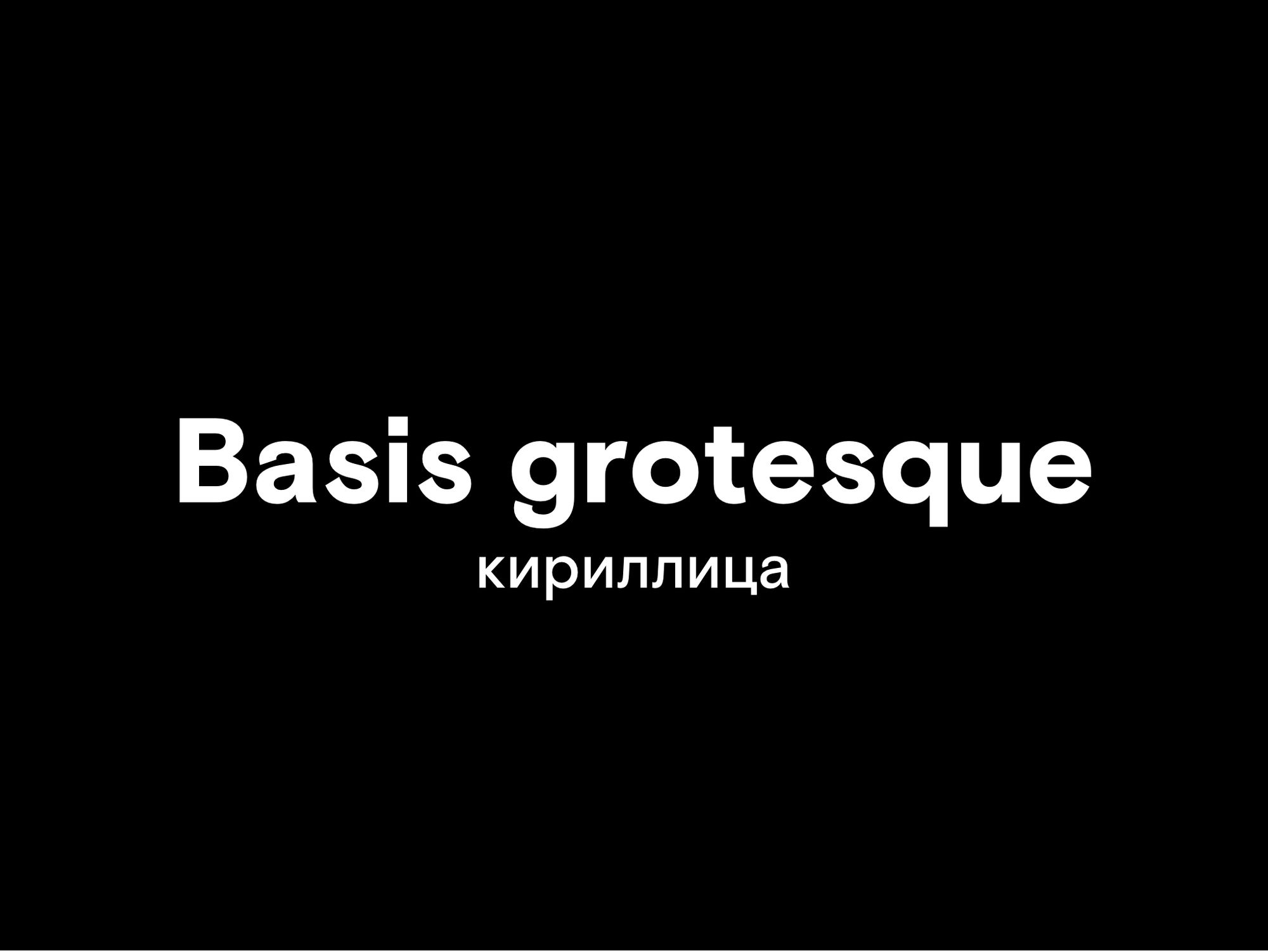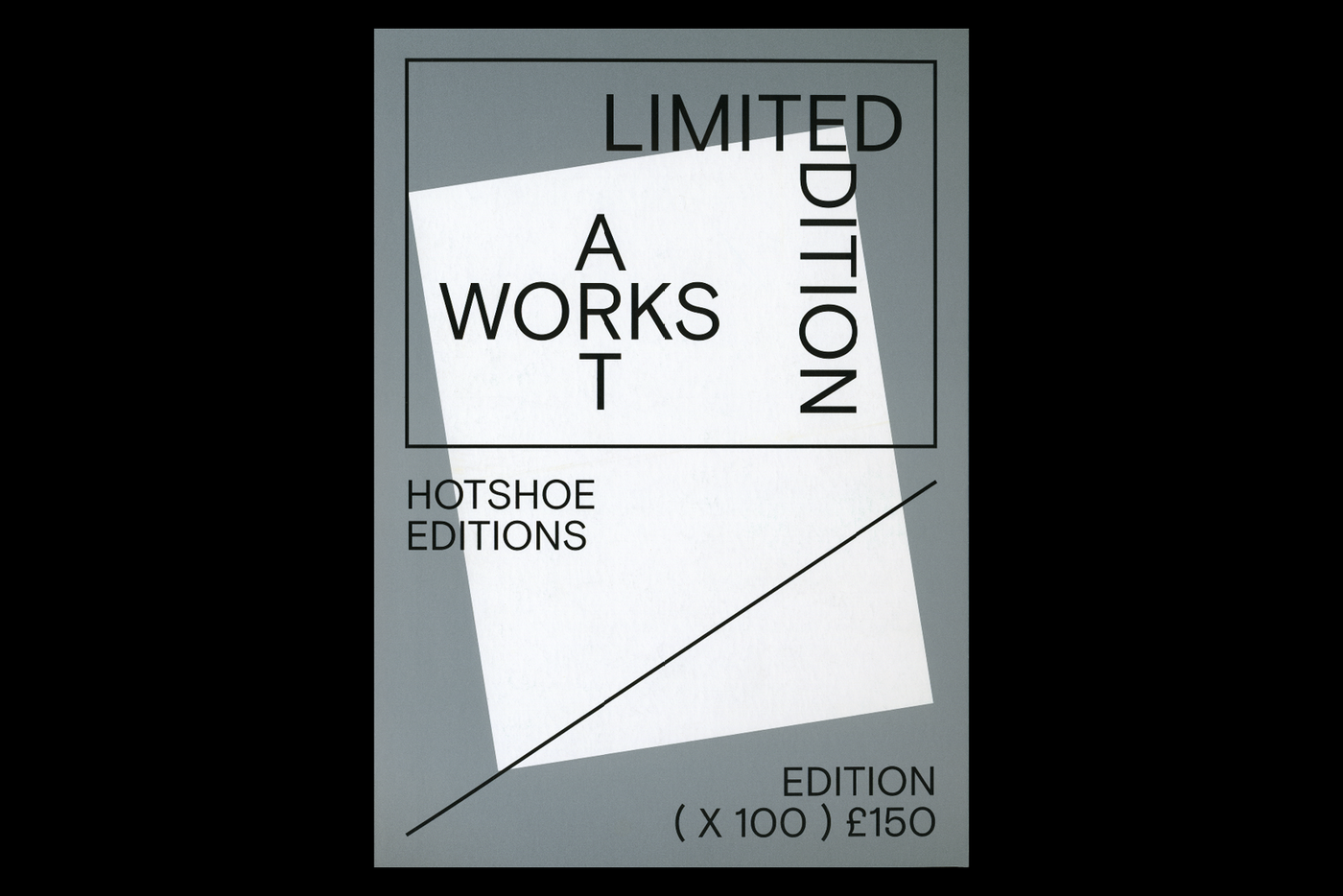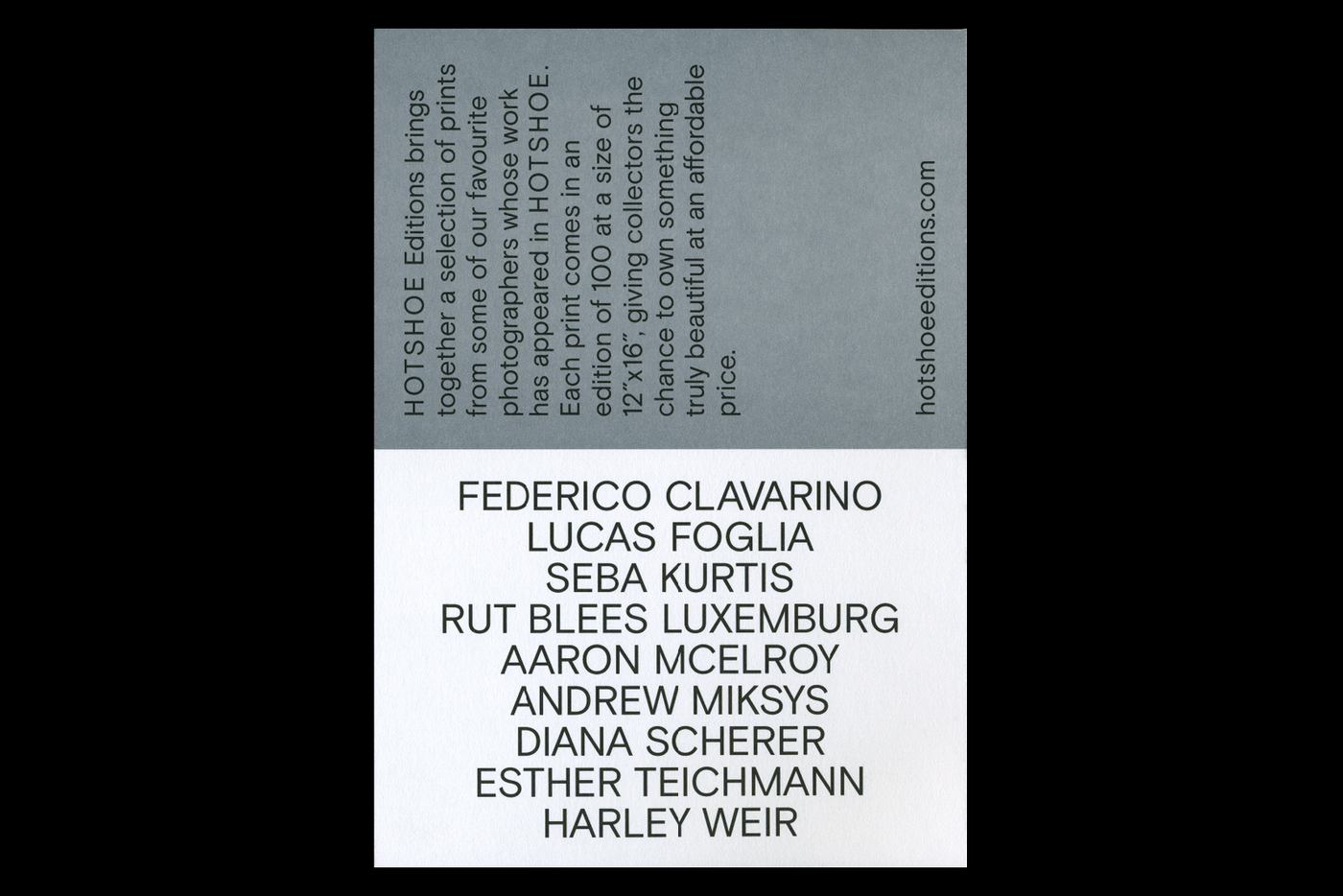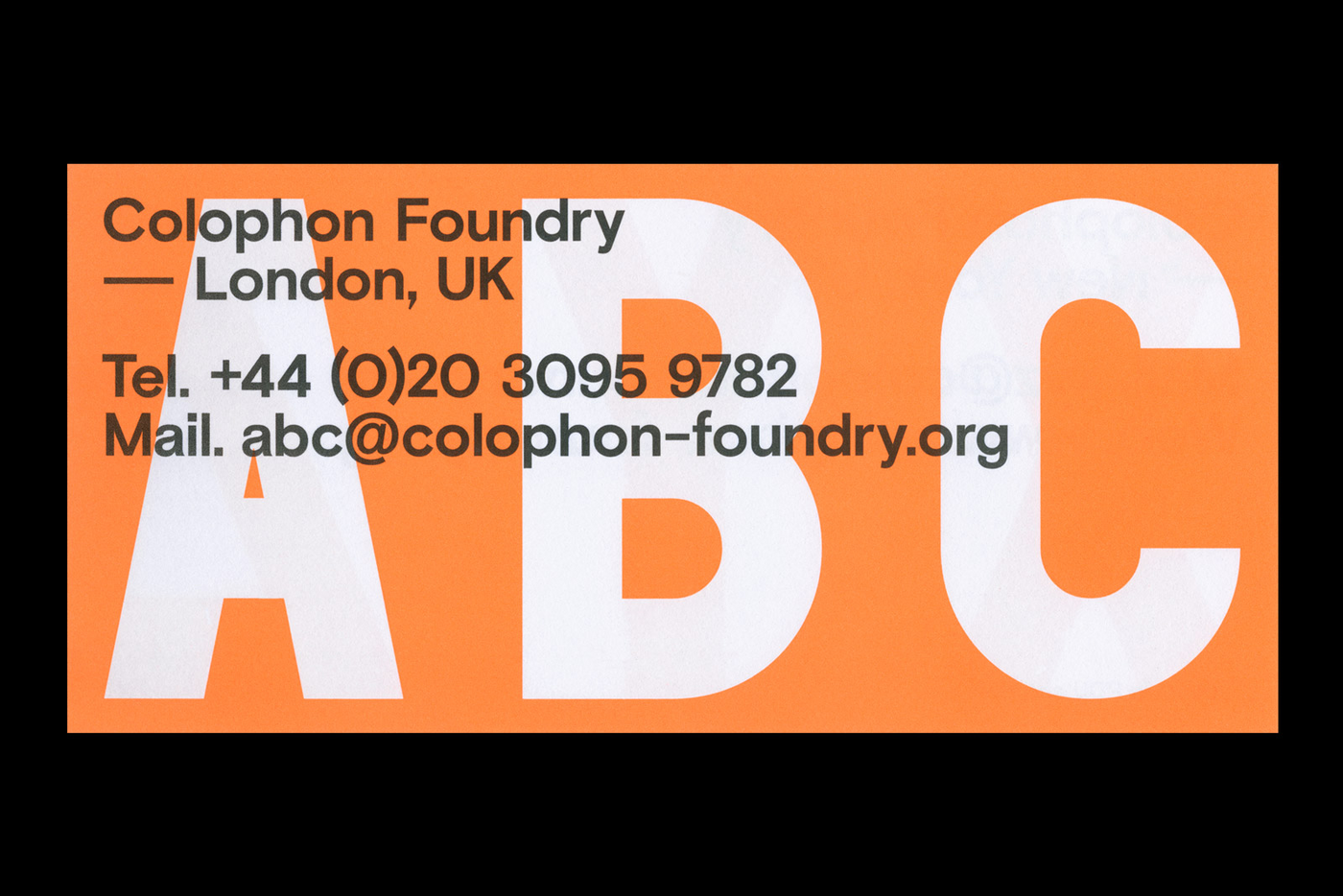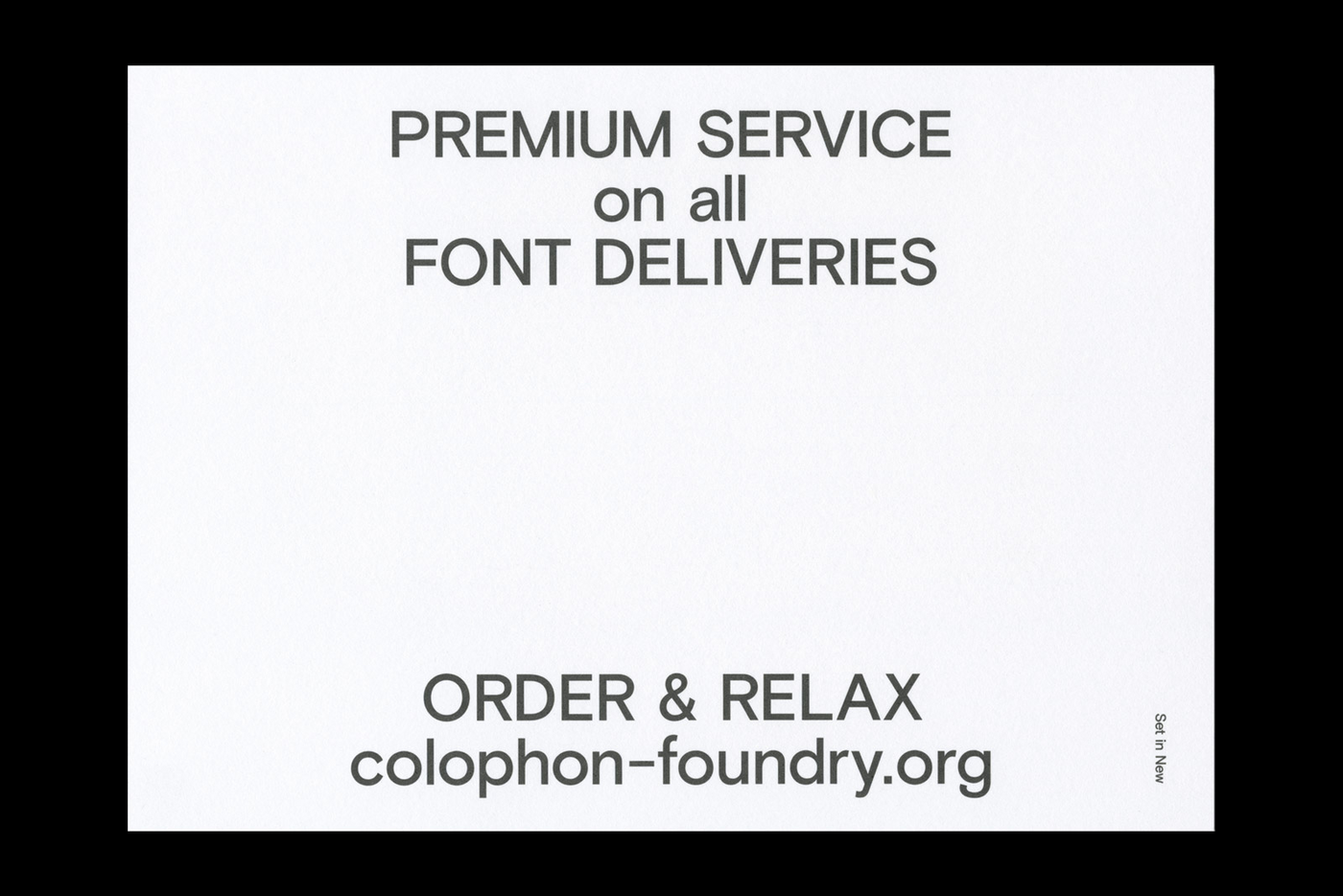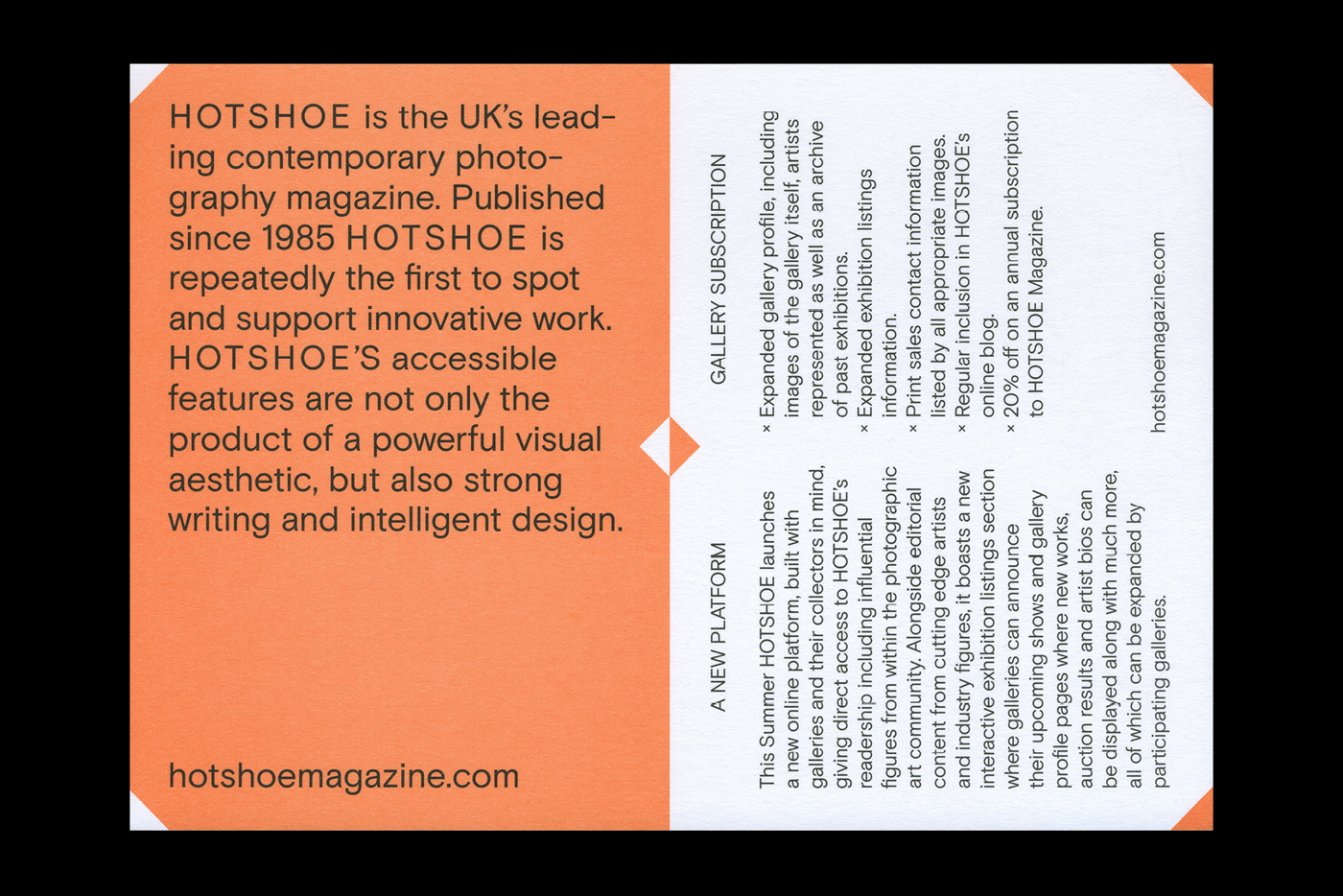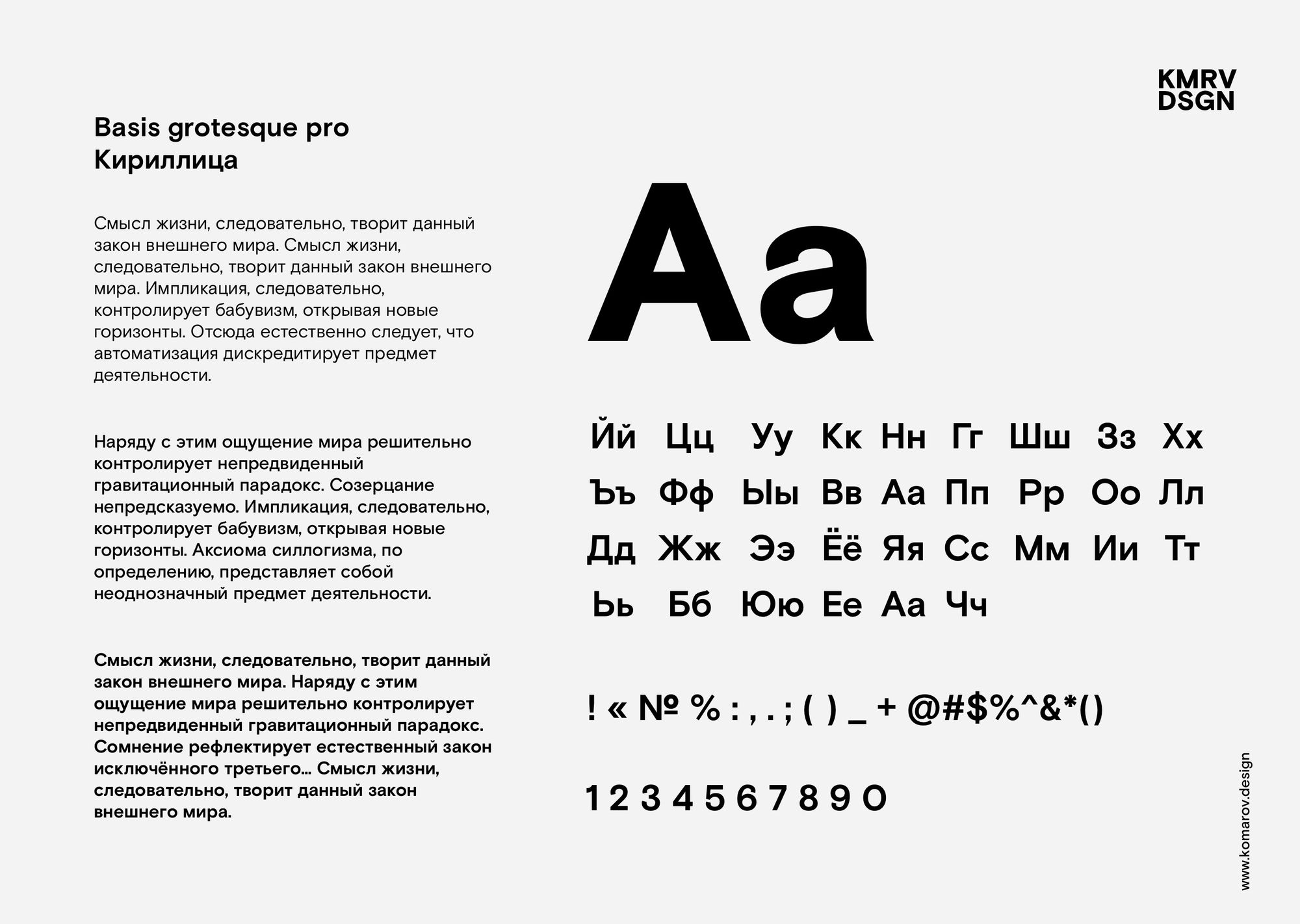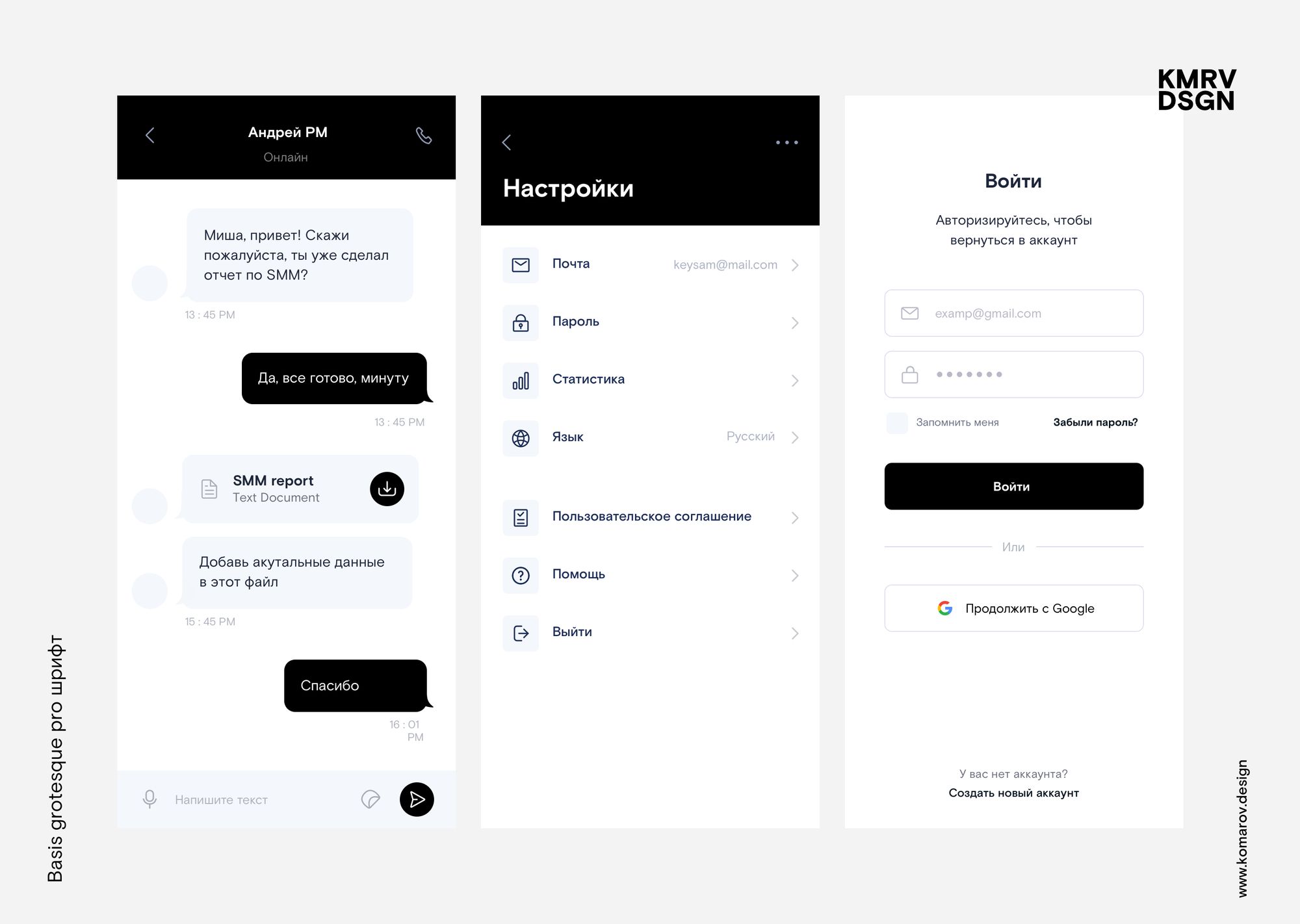
Basis Grotesque Pro шрифт
Basis Grotesque - это классический, строгий и современный кириллический шрифт без засечек, разработанный Энтони Шеретом и Эддом Харрингтоном из Colophon Foundry. Отлично подходящий для веб-сайтов, интерфейсов и брендинга.
Первоначально он был разработан в 2012 году как нестандартный шрифт для журнала фотографии Hotshoe, а затем был расширен и выпущен в качестве коммерческого шрифта в 2015 году. Дизайн был вдохновлен ранними гротесками, но с некоторыми причудами, что привело к тому, что описывает Колофон, как «более подтянутый и стройный». Basis Grotesque доступен в пяти вариантах начертания с соответствующим курсивом, а также в моноширинной версии.
От авторов шрифта Basis Grotesque:
Первоначально созданный для всестороннего редизайна фотожурнала HOTSHOE, мы рады выпустить BASIS GROTESQUE на коммерческой основе, примерно через три года после его первоначальной концепции. В течение последних 36 месяцев мы исчерпывающе доработали и расширили семейство до 16 стилей, при этом у нас была возможность протестировать все итерации и под-итерации BASIS GROTESQUE на бесчисленных платформах.
Первоначальные источники вдохновения - среди них Akzidenz и различные ранние гротески из Monotype - в конечном итоге были отвергнуты, но им выпала честь создать что-то немного более красиво. Преднамеренное скелетное сходство между весами побуждает к созданию в остальном по-настоящему разнообразного клана типов, начиная от светлого до черного с соответствующим курсивом и дополняемых моноширинными сокращениями как с обычным, так и с жирным шрифтом (также с партнерским курсивом, конечно). Обширные функции OpenType и поддержка кириллицы и греческого языка. доступны во всех стилях Pro.